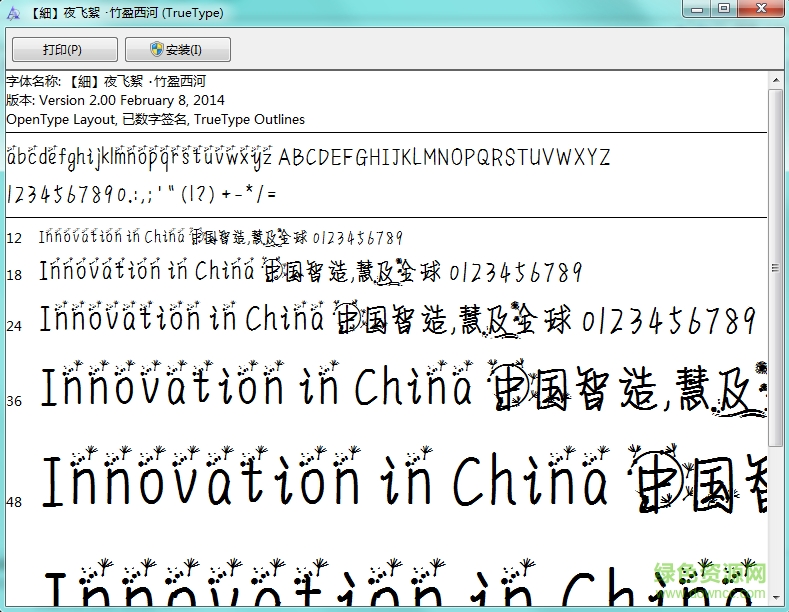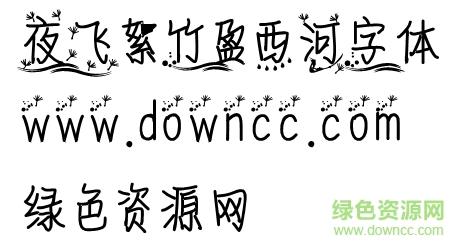
竹盈西河字體是一款非常浪漫活潑的pop字體,輕柔的柳絮飛舞在文字間,是最明媚的季節(jié)的一抹亮色,喜歡的朋友看就來綠色資源網(wǎng)嘗試吧!
竹盈西河字體取材于常見的春城飛絮美景,讓文字?jǐn)[脫了單一的閱讀性,獲得了如臨其境的美感,是一款獨(dú)特的藝術(shù)字體,字條纖細(xì)筆觸輕柔,沉睡著一個(gè)不為人知的夢(mèng)。
字體是以一款硬筆手寫字體為原形。在字體間又加入了圖案裝飾,看上去非常可愛,趣味實(shí)足。特別適合喜歡卡通的朋友在手機(jī)上安裝使用。